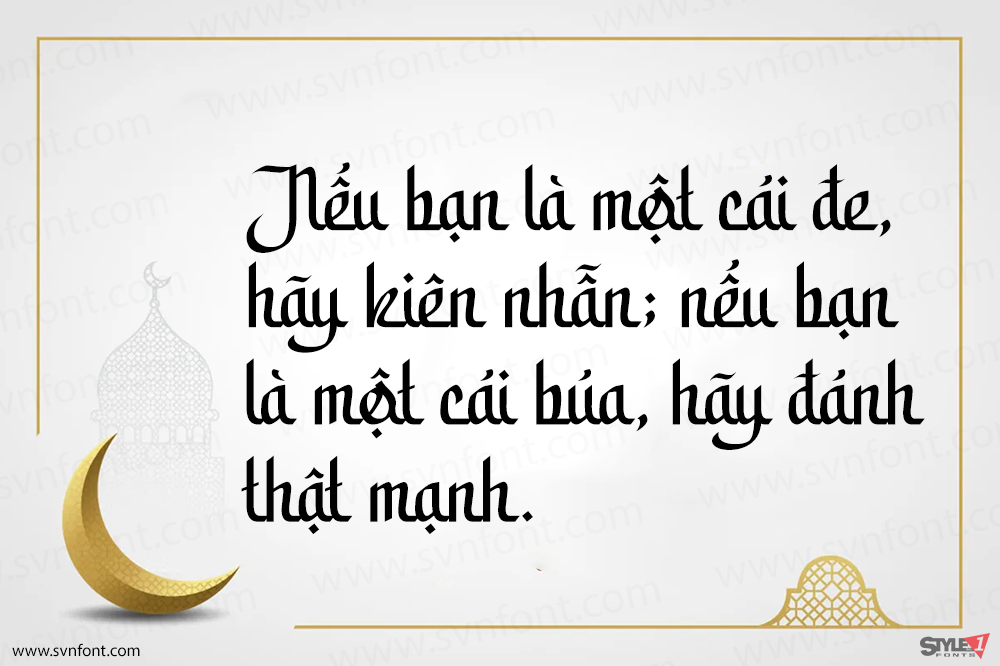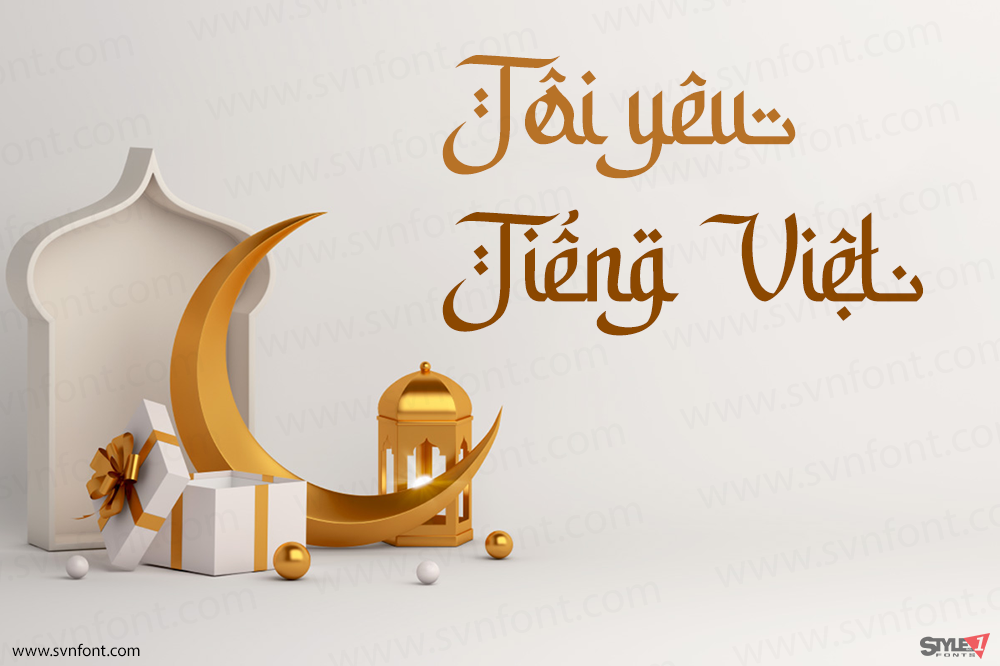
Giới thiệu Phông Chữ Phong Cách Ả Rập Alamsyah Mới của chúng tôi, rất phù hợp để tạo ra những lời mời đáng yêu cho đám cưới, sinh nhật, ngày đặc biệt. Một tập hợp các chữ cái và số phù hợp với các dự án của bạn, cũng tuyệt vời cho Thiết kế Logo, Thiết kế Thương hiệu, Nghệ thuật Chữ Kỹ Thuật Số, Áo Thun/Trang phục, Áp phích, Tạp chí, Biển hiệu, Thiết kế Quảng cáo và cũng hoàn hảo cho việc xây dựng thương hiệu các dự án khác của bạn.